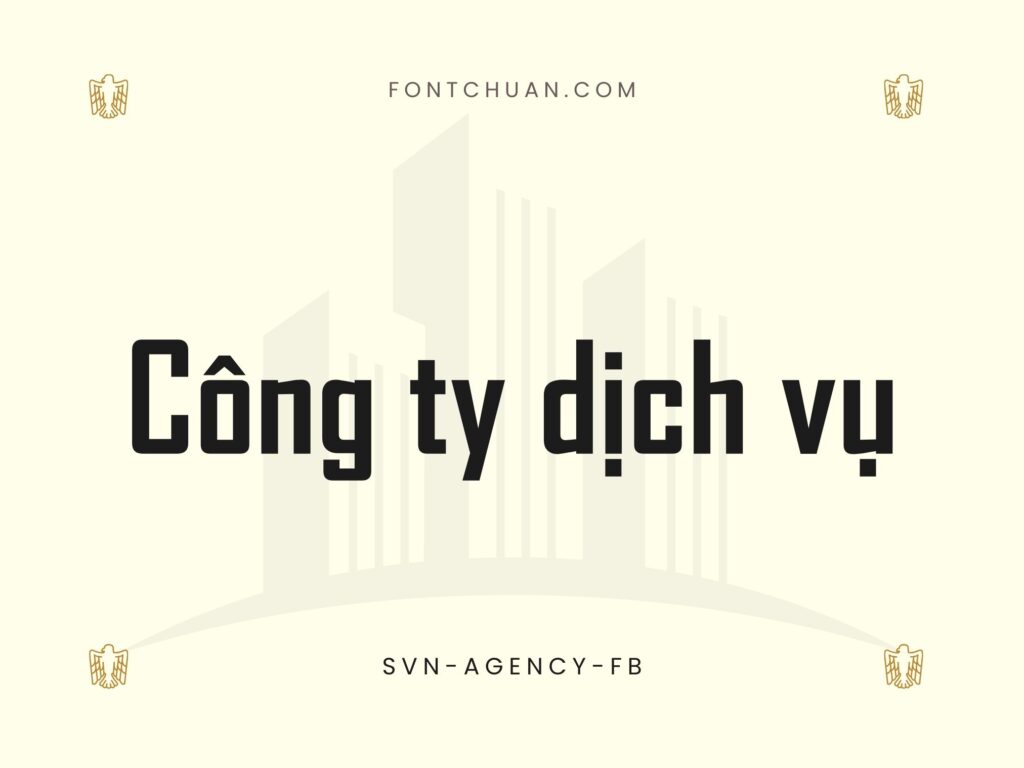
Font SVN Agency FB là phiên bản Việt hóa của kiểu chữ Agency FB, được thực hiện bởi Styleno.1 Fonts. Agency FB là một kiểu chữ sans-serif được thiết kế bởi The Font Bureau, Inc., nổi bật với các đường nét hẹp và góc cạnh, tạo cảm giác hiện đại và mạnh mẽ. Font này thường được sử dụng trong các thiết kế yêu cầu sự rõ ràng và chuyên nghiệp.
SVN Agency FB lý tưởng cho các dự án thiết kế logo, tiêu đề, bao bì sản phẩm và các ấn phẩm quảng cáo. Các ngành nghề như quảng cáo, giáo dục và công nghệ có thể tận dụng font này để tạo điểm nhấn trong thiết kế. Ngoài ra, font cũng thích hợp cho các sự kiện như Tết, Giáng sinh, Valentine và các lễ hội khác.